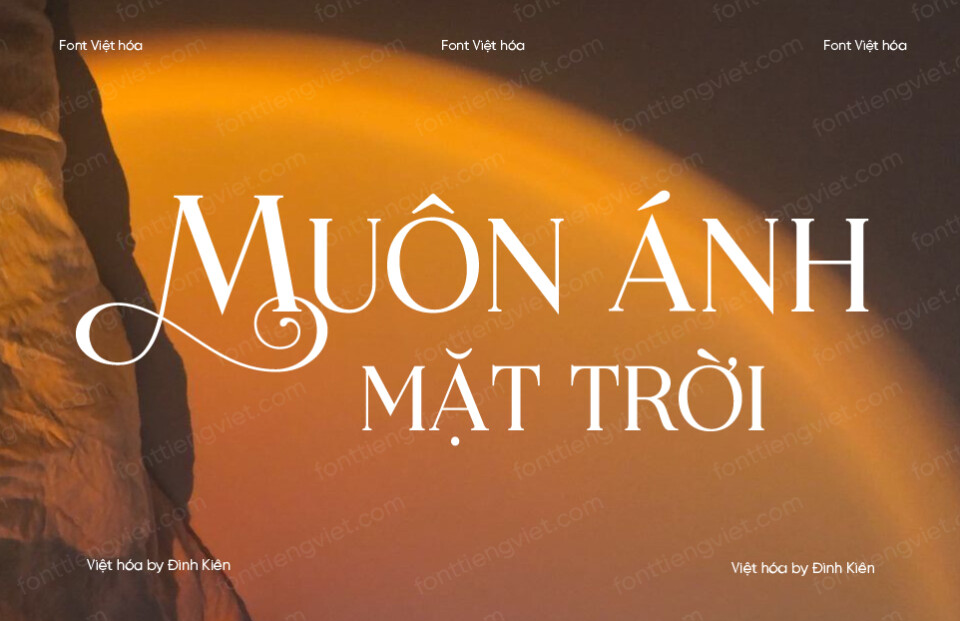
Tải và Sử Dụng Font Việt hóa UTM Encore Cho Đồ Họa và Luận Văn Tốt Nghiệp
Trong thế giới thiết kế đồ họa và soạn thảo văn bản, việc lựa chọn một Font Chữ phù hợp đóng vai trò vô cùng quan trọng, đặc biệt đối với học sinh, sinh viên và những người đang chuẩn bị cho các kỳ thi tốt nghiệp hoặc làm luận văn. Hôm nay, chúng ta sẽ đi sâu vào tìm hiểu về Font Việt hóa UTM Encore – một trong những bộ font được cộng đồng thiết kế Việt Nam yêu thích. Đây không chỉ là một phông chữ đẹp mắt mà còn là giải pháp hoàn hảo cho các dự án đòi hỏi tính thẩm mỹ cao và độ dễ đọc tuyệt vời, giúp nâng cao chất lượng các tài liệu học thuật và chuyên môn của bạn.
Việc sử dụng các font chữ chuẩn và chuyên nghiệp như UTM Encore giúp bài làm của học sinh trung học, sinh viên đại học trở nên ấn tượng và dễ dàng đạt điểm cao hơn trong các bài kiểm tra, bài thuyết trình, hay các dự án lớn như đồ án tốt nghiệp. Chúng ta sẽ cùng khám phá tại sao bộ font này lại trở thành lựa chọn hàng đầu cho giới trẻ Việt Nam.
Giới Thiệu Về Font Việt hóa UTM Encore
Bộ font UTM (Union Typeface Mechanism) là một dự án lớn nhằm cung cấp các phông chữ chất lượng cao, được thiết kế riêng biệt để tương thích hoàn hảo với ngôn ngữ Tiếng Việt. Trong số đó, Font Việt hóa UTM Encore nổi bật như một phiên bản được cải tiến và tối ưu hóa cao. Được xây dựng dựa trên các nguyên tắc typography hiện đại, UTM Encore mang lại sự kết hợp hài hòa giữa nét truyền thống và hơi thở đương đại.
Sự ra đời của các bộ font Việt hóa như UTM Encore đã giải quyết triệt để vấn đề lỗi hiển thị dấu tiếng Việt mà nhiều font quốc tế khác mắc phải. Đối với sinh viên đang làm luận văn tốt nghiệp hoặc các tài liệu chính thức, việc có một bộ font chuẩn xác về mặt kỹ thuật là điều kiện tiên quyết để đảm bảo tính chuyên nghiệp và tính toàn vẹn của nội dung.
Nguồn Gốc và Ý Nghĩa Của Tên Gọi Encore
Cái tên Encore (nghĩa là “hãy làm lại lần nữa” hoặc “lời yêu cầu trình diễn thêm”) ngụ ý về sự hoàn thiện, sự trở lại đầy ấn tượng của một sản phẩm chất lượng. UTM Encore thực sự đã tạo nên một dấu ấn mạnh mẽ trong cộng đồng thiết kế, được sử dụng rộng rãi từ các ấn phẩm in ấn, logo thương hiệu cho đến giao diện website và tài liệu học thuật.
Đặc Điểm Nổi Bật Của Bộ Font UTM Encore
Không phải ngẫu nhiên mà UTM Encore được nhiều người yêu thích, đặc biệt là các bạn học sinh, sinh viên chuyên ngành thiết kế đồ họa. Bộ font này sở hữu những đặc điểm vượt trội giúp nó khác biệt so với nhiều lựa chọn khác trên thị trường.
Phong Cách Thiết Kế Thanh Lịch và Dễ Đọc
UTM Encore được thiết kế với các đường nét rõ ràng, tỷ lệ hợp lý và khoảng cách ký tự (kerning) được căn chỉnh tỉ mỉ. Điều này không chỉ tạo nên tính thẩm mỹ cao mà còn đảm bảo khả năng đọc tốt ngay cả khi sử dụng ở kích thước nhỏ hoặc trong các đoạn văn dài. Đây là yếu tố then chốt cho các tài liệu học tập, báo cáo khoa học, và đặc biệt quan trọng trong các tài liệu cần chuẩn bị cho kỳ thi tốt nghiệp.
Bộ font này thường có nhiều trọng lượng (weights) khác nhau, từ Light (nhẹ) đến Bold (đậm), cho phép người dùng linh hoạt lựa chọn phong cách phù hợp cho các tiêu đề (headers) và nội dung chính (body text) trong cùng một dự án.
Khả Năng Việt Hóa Chuẩn Xác và Đa Dạng
Điểm mạnh lớn nhất của Font Việt hóa UTM Encore là khả năng hiển thị tiếng Việt hoàn hảo, không gặp bất kỳ lỗi font nào liên quan đến dấu câu, dấu thanh. Các ký tự đặc trưng của tiếng Việt như ă, â, đ, ê, ô, ư được thiết kế đồng bộ với các ký tự Latin cơ bản, mang lại trải nghiệm đọc mượt mà và chuyên nghiệp tuyệt đối. Đây là một lợi thế cực lớn đối với các bạn trẻ đang phải hoàn thành các bài thi hoặc luận án bằng tiếng Việt.
Ứng Dụng Của UTM Encore Trong Học Tập và Thiết Kế
Với độ linh hoạt cao, UTM Encore được ứng dụng rộng rãi trong nhiều lĩnh vực, từ học đường cho đến môi trường làm việc chuyên nghiệp.
- Luận Văn Tốt Nghiệp và Đồ Án: Font UTM Encore mang lại vẻ ngoài nghiêm túc, chuyên nghiệp, rất thích hợp để trình bày nội dung trong các luận văn, khóa luận, hay các báo cáo nghiên cứu khoa học. Sự rõ ràng của font giúp người chấm dễ dàng theo dõi và đánh giá cao tính chỉn chu của bài làm.
- Bài Thuyết Trình (PowerPoint/Keynote): Các phiên bản đậm của UTM Encore rất hiệu quả khi làm tiêu đề slide, thu hút sự chú ý của người nghe. Phong cách thanh lịch cũng giúp nội dung không bị rối mắt.
- Thiết Kế Poster và Brochure: Trong các hoạt động ngoại khóa, câu lạc bộ học sinh, sinh viên, việc sử dụng font này giúp các ấn phẩm truyền thông trở nên hấp dẫn hơn, đồng thời giữ được sự chuyên nghiệp cần thiết.
- Soạn Thảo Sách Giáo Khoa/Tài Liệu Học Tập: UTM Encore đảm bảo độ dễ đọc cần thiết cho việc học, giảm thiểu mệt mỏi thị giác khi phải tiếp xúc với văn bản trong thời gian dài.